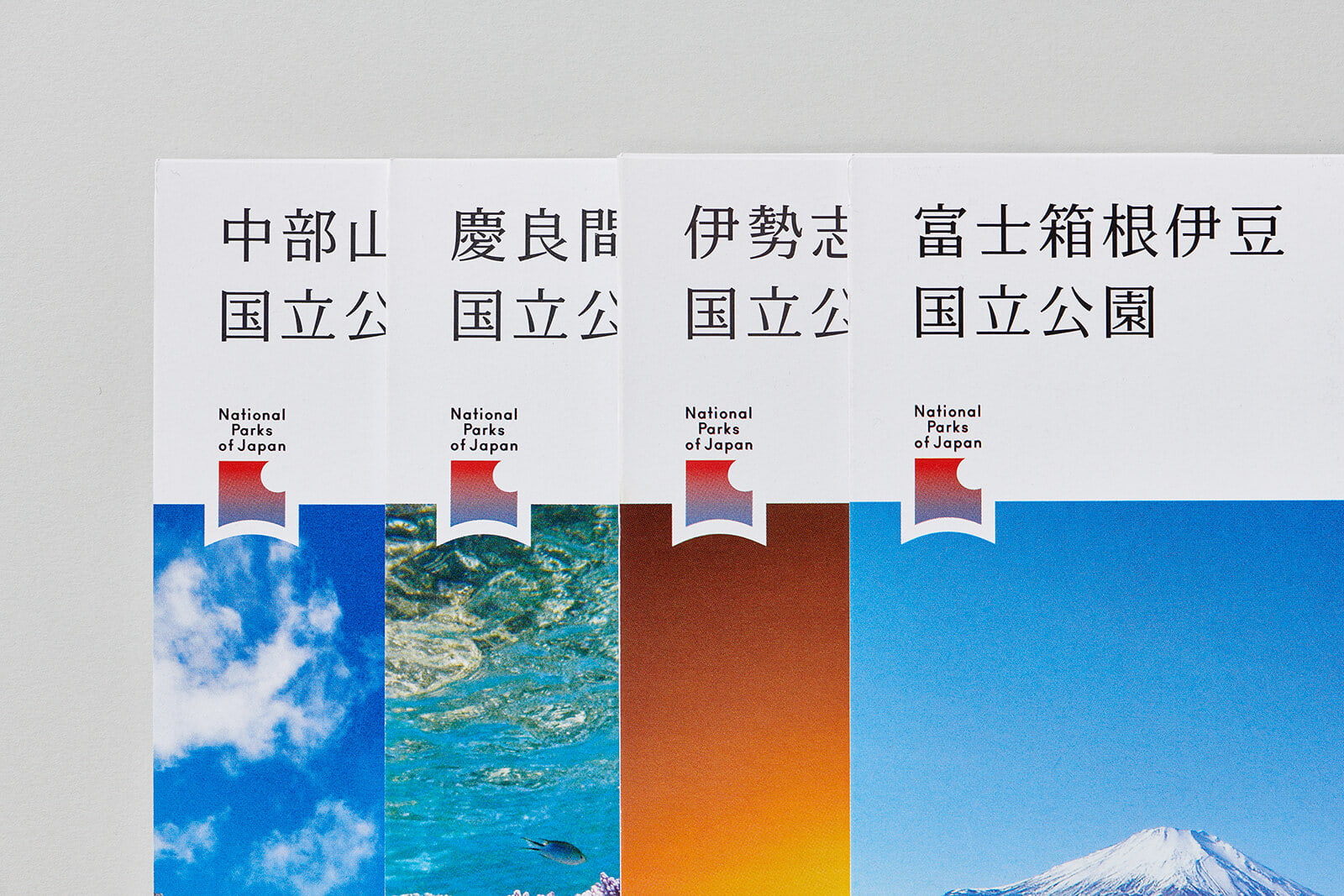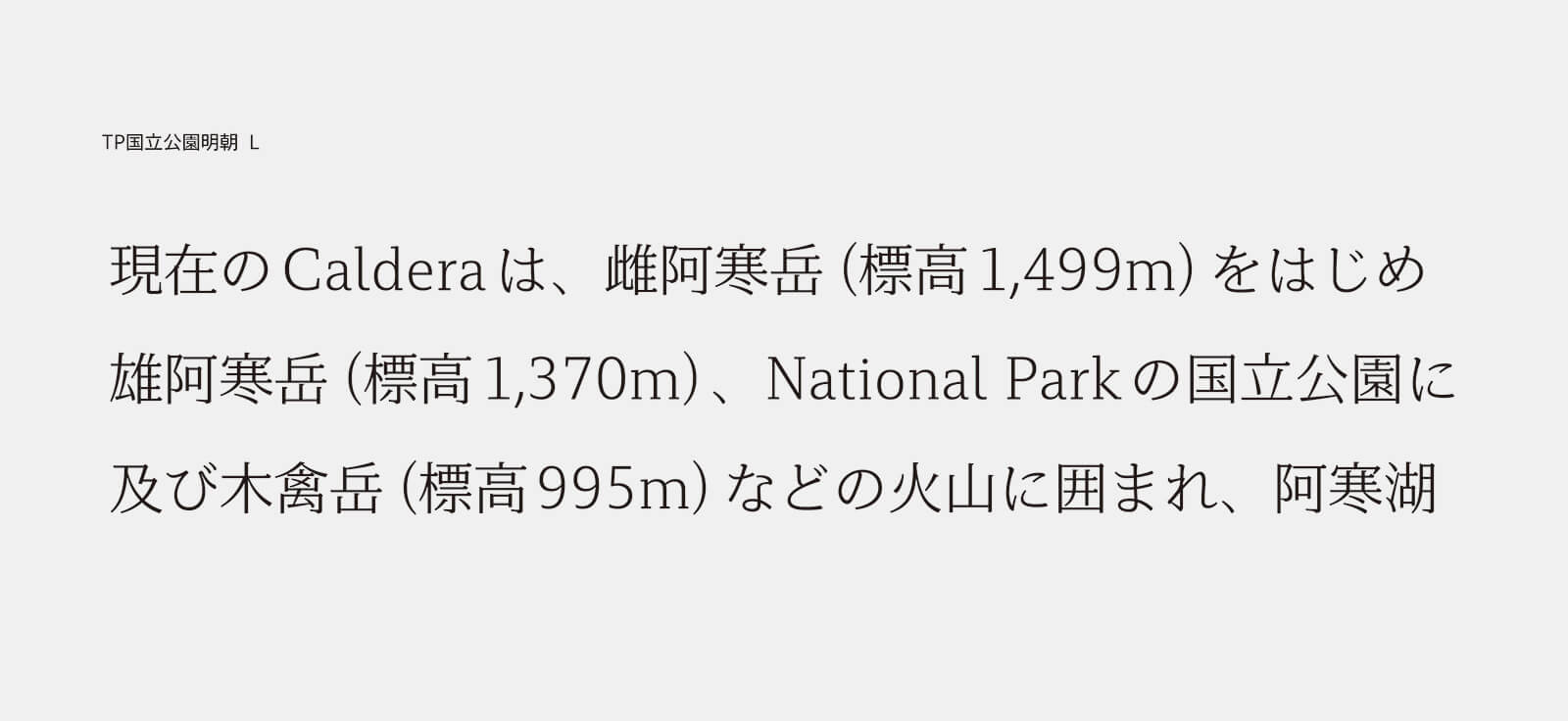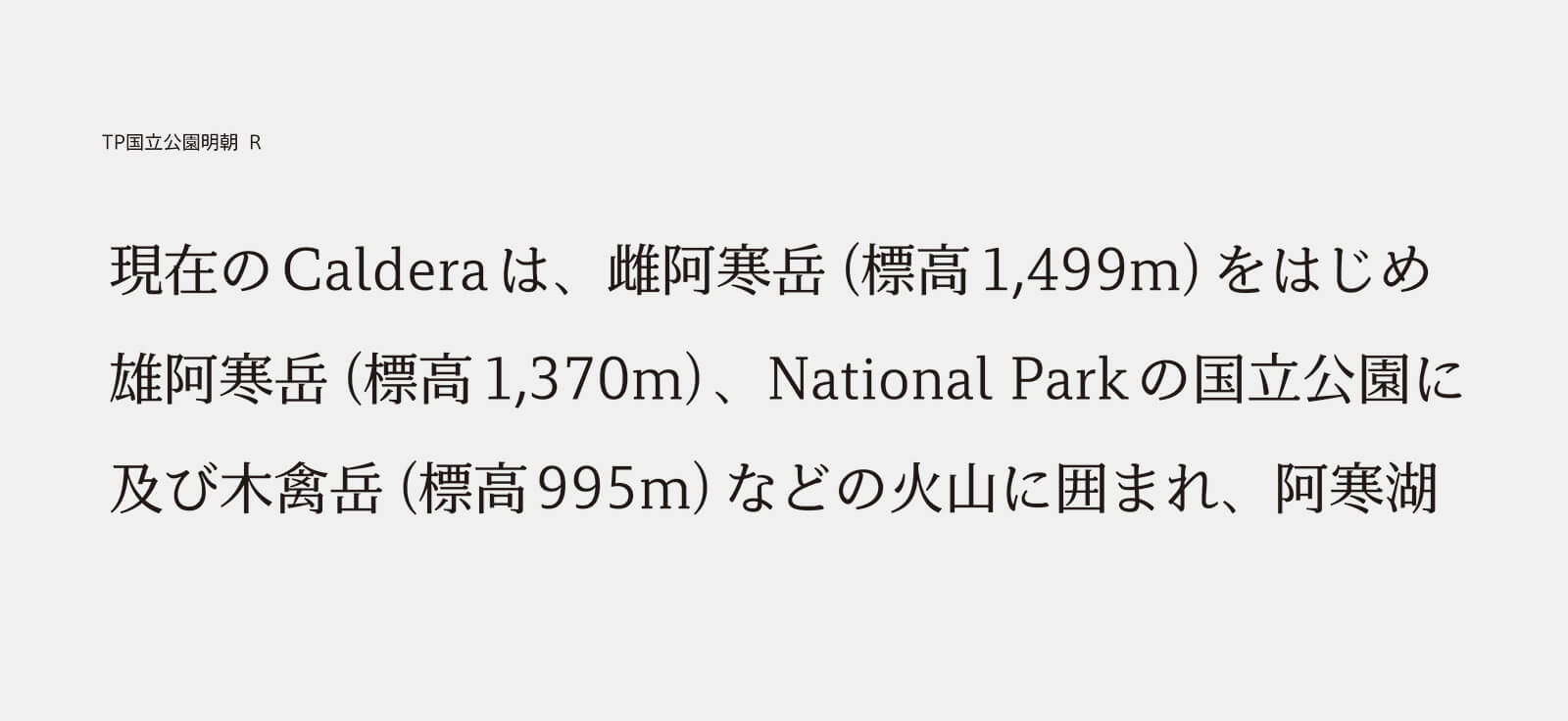
タイププロジェクト、環境省に国立公園用専用フォント「TP国立公園明朝」を提供
全国の国立公園で使用予定、オンラインショップで一般販売も開始
タイププロジェクト株式会社 (東京都練馬区 代表取締役社長 鈴木 功、以下 タイププロジェクト) は、環境省向けに、オリジナルデザインの欧文書体とTP明朝を組合せた国立公園専用フォント「TP国立公園明朝」を提供したことを発表しました。合わせて、TPコネクトでの提供とオンラインショップでの一般販売も開始いたします。
TP国立公園明朝は、環境省により2016年にスタートした「国立公園満喫プロジェクト」の一環として開発が始まりました。「日本の国立公園らしい品格や風合いを持ちつつ、看板等に使用した際の視認性を確保する」という要望の元に提供したTP国立公園明朝は、現代的な骨格を持ったスラブセリフフォント*です。TP国立公園明朝の和文部にはTP明朝のローコントラストを採用し、欧文フォントを新たに開発しました。
(*スラブセリフフォント:セリフ部分が直線的で、縦横のストロークとセリフの太さの差が小さい書体)
TP明朝は、明朝体に横画と縦画の太さの比率を自由に変えられるコントラストという概念を導入した、初めての日本語フォントです。TP明朝のローコントラストは、ゴシック体を思わせる線率をもち、従来の明朝体と比べて横画が太いため、視覚的なインパクトが大きく誘目性に優れています。
タイププロジェクトの代表取締役 鈴木 功は、「TP明朝ローコントラストは、ディスプレイ上で自然に読める明朝体として開発しました。その設計コンセプトは同時に、サインシステムにも最適だと自負しています。また、横画が消えにくいという特徴は、パンフレットや名刺などの小さなサイズで使用した際にも効果を発揮します」と述べています。
新規に開発した欧文書体は、国立公園統一マークや標識整備、パンフレット等、国立公園のブランディングを担当した日本デザインセンターのアートディレクター色部義昭氏と、タイププロジェクトが協議を重ねて開発しました。TP明朝ローコントラストの設計を共有するとともに、和文書体との調和を重要視するため、ウエイトやコントラストをほんのわずかに太くすることで混植の際のフラットな印象を生み出していますので、遠くからの視認性にも優れ、サインシステムに最適です。
環境省国立公園利用推進室では、「政府全体として推進する『明日の日本を支える観光ビジョン』の取り組みの中で、日本の国立公園を『世界水準のナショナルパーク』としてのブランド化をすすめています。その中で、今回のTP国立公園明朝は、訪日外国人にとっても違和感のない欧文フォントになったことを喜ばしく思っています」と述べています。